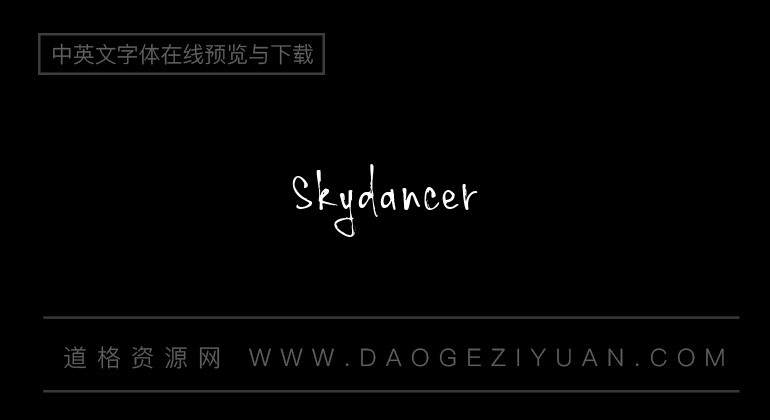
Skydancer
Skydancer 是一款由荷兰设计师Pieter van Rosmalen设计的英文字体,它是一种拉丁文字体,具有流畅的线条和圆润的字形,适用于大多数文本和标题文本。Skydancer字体拥有细节丰富的设计,使其成为一款非常适用于报纸、杂志、海报和网页等多种文本媒体的字体。Skydancer字体具有优雅的外观和精致的细节,使其成为一款非常适用于报纸、杂志、海报和网页等多种文本媒体的字体。这款字体的特点是它具有较强的可读性,可以清晰地传达文字的意思,并且具有较强的视觉冲击力,使文本更加有吸引力。
Skydancer是一款非常不错的手写艺术字体,具有很好的视觉感,适合于文化类的宣传设计、商业类品牌的广告和产品包装设计以及个性化文字排版等较多场景。